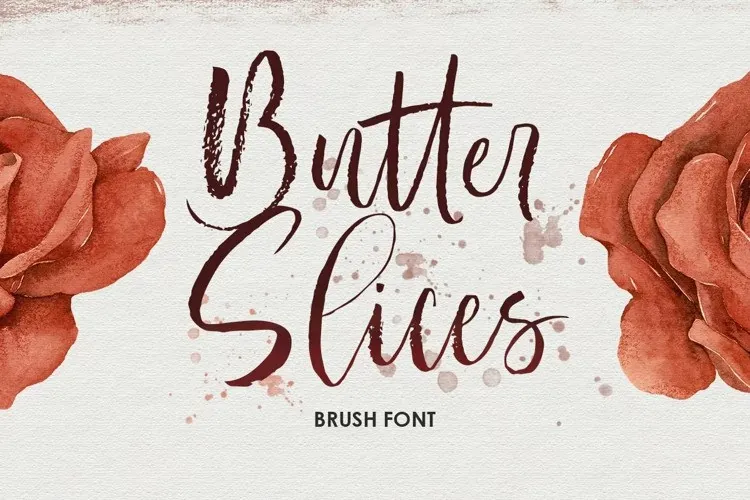
Butter Slices Font – Download Grátis
A fonte ‘Butter Slices’ é uma tipografia script baseada em uma espiral de caneca elegante e delicada. Inspirada na arte fluida do desenho com swashes, a Butter Slices faz da sua aparição um ato de desejo aos olhos. Este tipo de fonte foi projetado para ser aplicado em inúmeros ambientes, incluindo convites de casamento, rótulos, logotipos, revistas e livros, cartões de agradecimento ou de casamento, embalagens, moda e maquiagem, materiais escolares, romances, rótulos ou qualquer tipo de propósito publicitário. Seja você um designer buscando uma fonte que brilhe nas páginas de um romance ou em um cartão de agradecimento especial, este é o tipo de fonte perfeito para deixar seu trabalho ainda mais sofisticado e apaixonante.